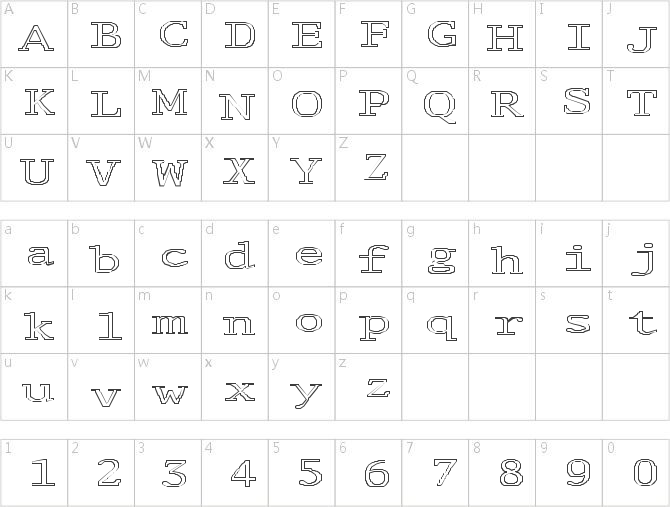
FZ DIGITAL 1 HOLLOW EX 詳情頁
FZ DIGITAL 1 HOLLOW EX字體字庫是一款讓人賞心悅目、百看不厭的英文字體,適合各類廣告和產(chǎn)品包裝設(shè)計(jì)應(yīng)用,字體大小0.11MB,格式為ttf字體,上傳用戶是我,Dirac,作者/版權(quán)方為未知